在传统图像处理方面,只是进行简单的颜色优化分割,但随着金融、互联网等各个行业的发展,人们需要的字体远远不止如此,需要更有行业和企业特色或个人特色,就如同人脸识别,需要有清晰的五官且可被别人清晰辨认和自动追踪,于是艺术字体下载行业兴起,那么为什么其中的字体美观度高呢?
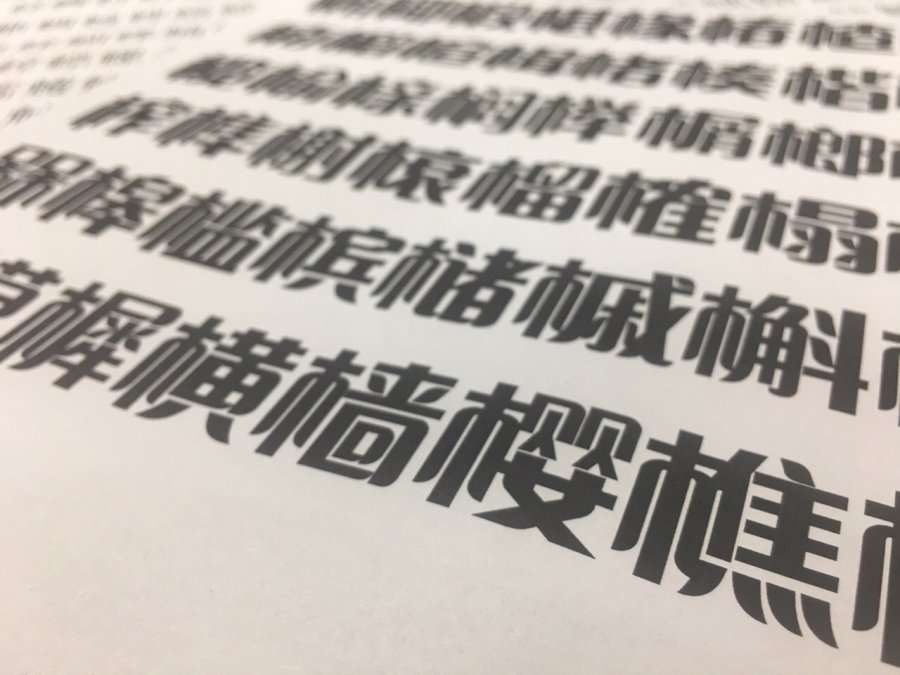
诸多艺术字中蕴含着故事,如果细致看,每个字都有笔画落地的过程,如许多艺术字体的线条往下、横线坠落,同样的设计感延续了不同的风格,这也是艺术字的协调和呼应,要尽量生成艺术字背后的故事,就是这个艺术字所表现的情感是什么内容?它所表现的情感是伤感、回忆亦或者开心愉悦,字体视界中不同的字体带来不同的情感感受。
可以抓住生活的体验和感受,这样在设计内容里发挥空间更大,设计出非常简单、非常纯的艺术字,甚至是一个没有经过修饰和更改的艺术字,建立内容越简单,才能够把你的情感表现的纯粹直接,如果加上太多华丽的变化,可能就没有那么简练了,艺术字可以掺杂一些图形,比如猫咪、鼠标、小花盆,猫咪字体比较慵懒舒适,把身边的一些元素提炼在艺术字体里边,表现在艺术字内,这样的艺术字能够作为一种记忆的形式,让它永久的保存下来。